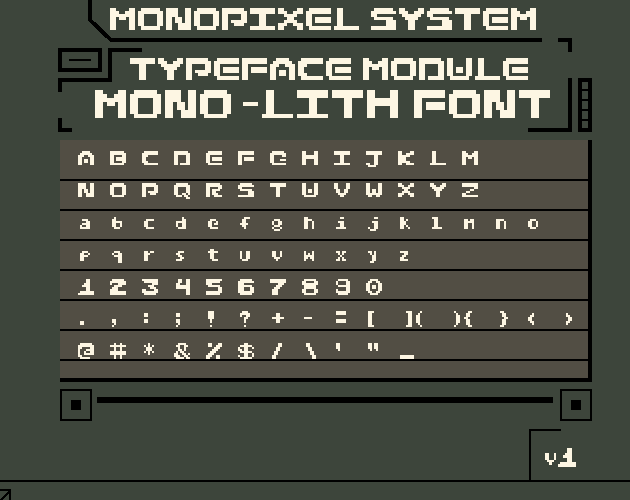
免费单体式MONO-LITH基础像素字体素材,一款高可读性的像素字体,专为复古工业风和未来主义界面而优化。
专为高强度用户界面环境而设计。它基于严格的几何网格,采用统一的 2px 字重,为工业、科幻和极简主义美学系统提供最大的清晰度。
- 功能设计:针对终端显示屏和HUD元素进行了优化。
- 模块化设计:可完美融入MONOPIXEL SYSTEM生态系统。
- 耐用性:即使在低分辨率下也具有很高的可读性。